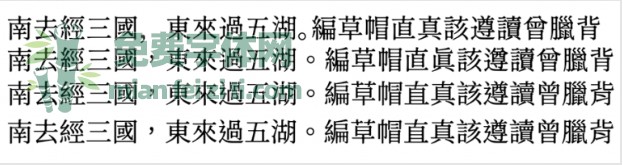
狮尾B2宋朝:思源宋体三角形转成半圆形改造
狮尾B2宋朝字体是把思源宋体的转角的三角形通过程序自动转成半圆形改造,就好像墨晕或是稍微过曝的效果。支持简体中文、繁体中文、韩文与日文;欢迎大家自由应用、自由优化、自由改作!
下面是源云明体JP、源云明体TW、思源宋体以及狮尾B2宋朝的比较效果。
下面这个图统计了这款字体里面包含多少个简体字数繁体字数等信息,方便大家直观地了解这款字体的简繁字体数量。